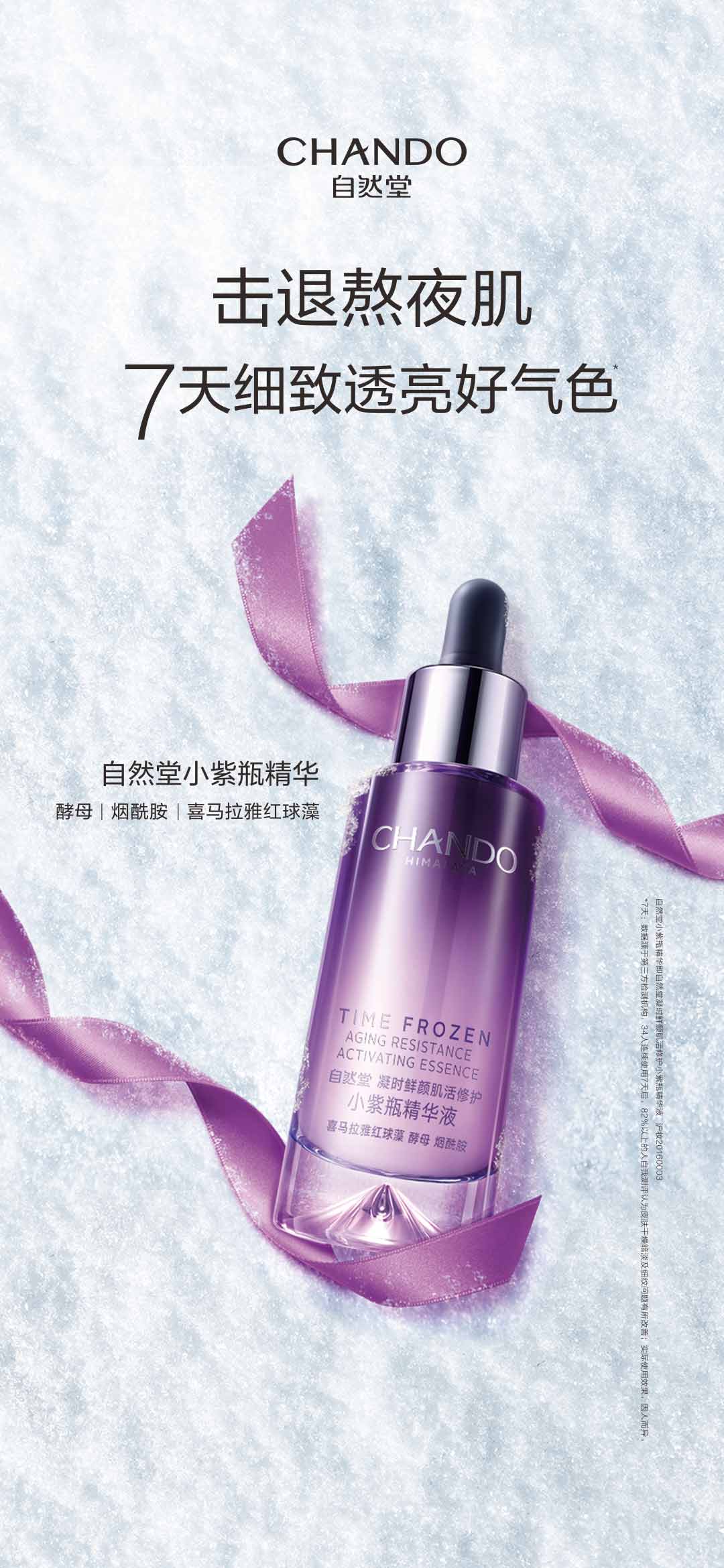
锐正圆家族是锐正黑家族的扩展与延伸,属性介于圆体与黑体之间,是适度中和的中性设计,既有圆体的圆润,又不失黑体的厚硬,柔中带锐、圆中有方。 笔形遵循书写性,做统一性规范化设计并增强镜像美感,介于方圆之间,太圆则易混沌不明快,太方则又刚硬欠流畅,旨在追求圆润柔美而又简洁明快。 字形趋于上圆下方、稳定中正,与中国“天圆地方”的传统理念相合,方圆结合、刚柔相济。 笔锋采用半圆角设计,相较黑体、圆体更具圆润兼锐化的时尚度,而太过夸张时尚又有失庄重,故而有意做适度收敛,圆融时尚而又端庄稳重,适用领域广泛。